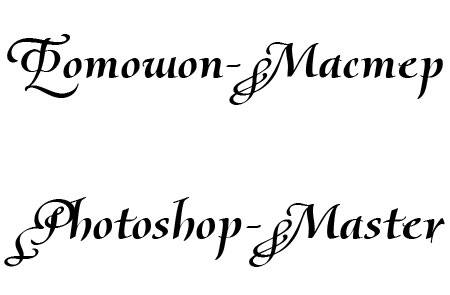
Симпотно.
Спасибо прекрасный шрифт, почти то что было нужно, немного векторе подправил, и получил желаемое:)
Супер шрифт.
Великолепный шрифт!
Красиво!
Вот этот очень симпатичный шрифт)
Круть!!!
Просто Супер!
Ух, ты какие завитушки, просто класс!
Даа, классно!
Классный) Спасибо, обожая такие завитушки)